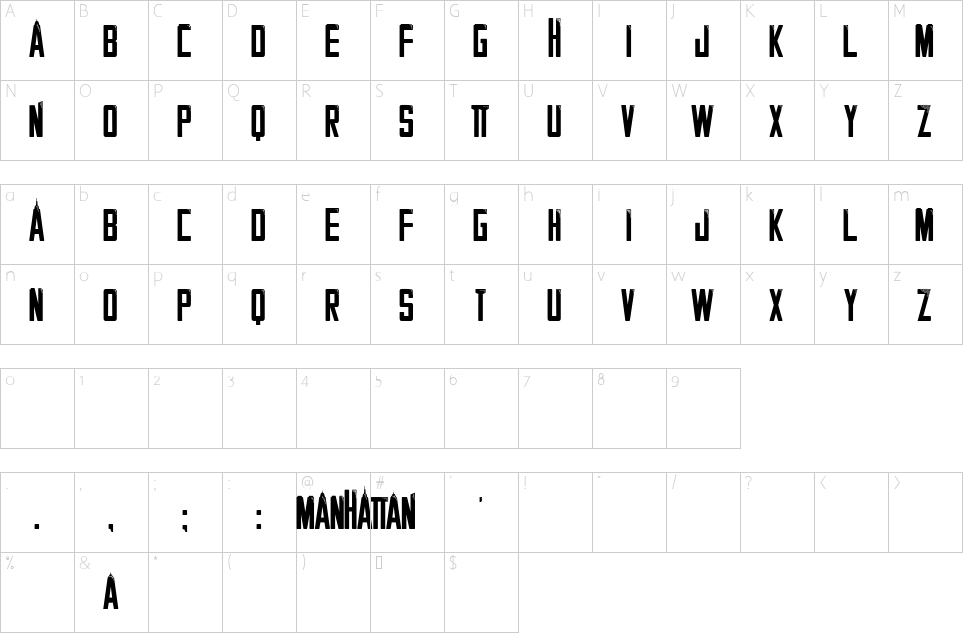
Descubra Manhattan font, uma elegante e sofisticada opção de fontes gratuita disponível para Windows e Mac. Lançada pelo designer Alphabet & Type, esta fonte gráfica foi projetada com cuidado para oferecer uma aparência atraente e versátil. Com seu design minimalista e arquitetônico, Manhattan é perfeita para gráficos e projetos que buscam um equilíbrio entre modernidade e elegância. Seu design fácil de ler e sua ampla gama de pesos e estilos garantem que seja uma escolha inteligente para qualquer projeto visual que deseje destacar. Com um design limpo e moderno, Manhattan é uma opção segura e conveniente para designers que buscam fontes únicas e fáceis de usar. Descubra por que mais de 9.545 pessoas já adquiriram Manhattan font. Descubra agora e adicione Manhattan à sua próxima criação.